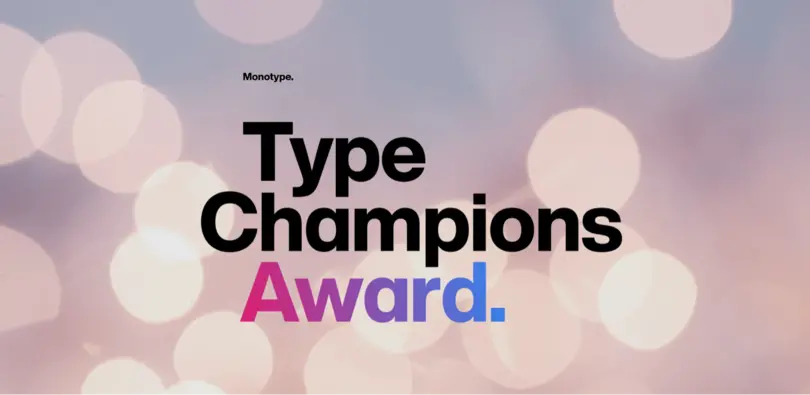
2019 Type Champions受賞者発表!
初年度のType Champions Award受賞者を発表いたします。Type Champions Awardは、書体を創造的、革新的かつ深い印象を刻む手法でブランドアイデンティティの構築に活用しているブランド企業を表彰する、Monotype主催の新しいプログラムです。
厳密な審査を経て、次のブランドが2019年の受賞者に選ばれました。
• & Other Stories
• Alibaba Group
• Audi
• Dropbox
• Juventus
• Mailchimp
• Ogilvy
• Southwest Airlines
• Squarespace
• The Guardian
• The New School
• The New York Times
Type Champions Award
Type Champions Awardは Monotype 主催のプログラムですが、世界中のブランディングおよびデザインの専門家からなる審査委員会の協力なしには実現できませんでした。審査には次のような方々にご協力いただきました。
• Rodney Abbot, Senior Partner, Lippincott
• Brian Collins, Chief Creative Officer and Founder, COLLINS
• Kirsten Dietz, Founder and Partner, Strichpunkt Design
• Chris Do, Founder, The Futur
• Perrin Drumm, Founder and Director, AIGA Eye on Design
• James Fooks-Bale, Creative Director, Monotype
• Mohamed Gaber, Founder, Kief Type Foundry
• Blake Howard, Co-Founder and Creative Director, Matchstic
• Patrick Märki, Managing Director, KMS Team
• Josh Miles, Chief Marketing Officer of SMPS and Host of Obsessed Show
• Abbott Miller, Partner, Pentagram
• Charles Nix, Type Director, Monotype
• Alejandro Paul, Type Designer, Co-Founder, Sudtipos
• Andy Payne, Global Chief Creative Officer, Interbrand
• Brett Zucker, Chief Marketing Officer, Monotype
2020年の書体トレンド
書体のデザイントレンドから、ブランド戦略の大きな流れが見えてきます。Monotypeはクリエイティブ業界の専門家や審査員の方々に、今日のデザインが未来へと導く傾向性について尋ねました。
1. 世界の言語への対応
2. バリアブルフォントの普及
3. ジオメトリックサンセリフの重要性
4. アイコンとしての書体: インラインとエングレービング
5. A.B.R. (リブランディング)
専門家からの引用
「 書体はブランドアイデンティティにおいて重要な役割を果たします。このアワードプログラムは、書体を活用して競合他社との差別化を図り、個性的で一貫性と関連性の高いブランドアイデンティティを築いている企業を表彰します" 」
James Fooks-Bale, Creative Director at Monotype.